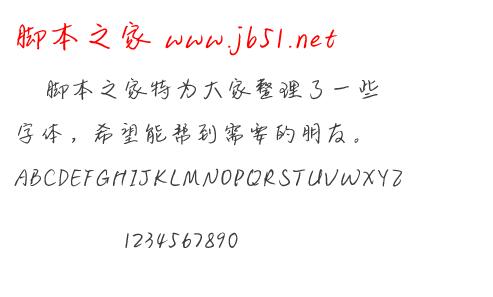
Aa告白氣球體是一款非常好看的手寫字體,這款字體有著鋼筆般書(shū)寫的風(fēng)格,并且筆畫(huà)流暢自然,每個(gè)字都處理的沉穩(wěn)簡(jiǎn)潔,不僅清晰可辨,還魅力十足。適合應(yīng)用于藝術(shù)設(shè)計(jì)、平面宣傳設(shè)計(jì)、網(wǎng)頁(yè)設(shè)計(jì),書(shū)法字